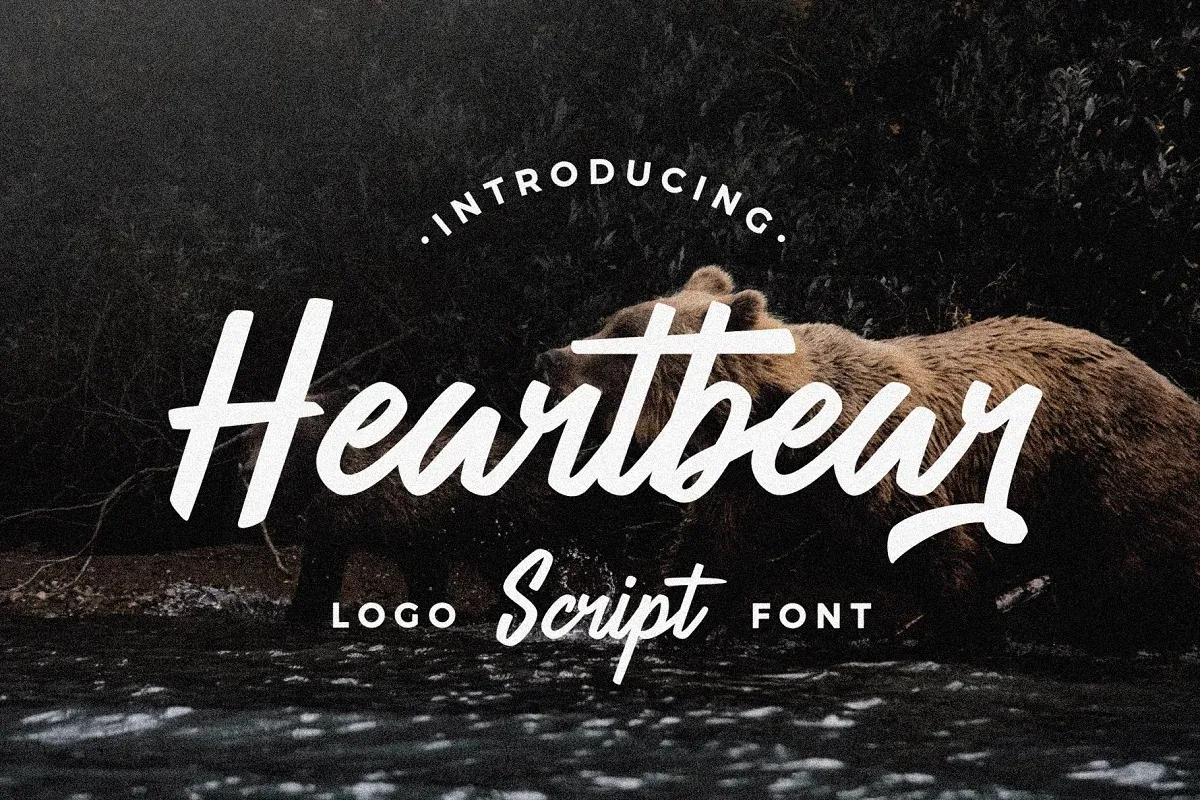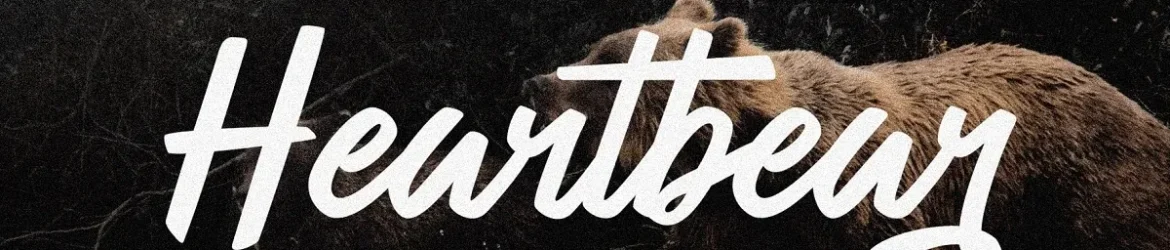
Heartbear Brush Font – Download Grátis
A Heartbear Brush Font é uma fonte script criada por HRDR com traços robustos, incluindo curvas arredondadas e traços levementes que adicionam um toque de personalidade e charme. Suas letras têm uma inclinação divertida e alguns ligamentos sutis para dar um toque especial ao texto. Esta fonte é perfeitamente adequada para a criação de invocações, logos de produtos, frases de citação ou até mesmo logomarcas de marcas alimentícias. Ela pode ser utilizada em diversas aplicações gráficas e tornará seus projetos de design mais elegantes. Esta fonte é perfeita para qualquer designer em busca de algo um pouco diferente no seu próximo projeto.